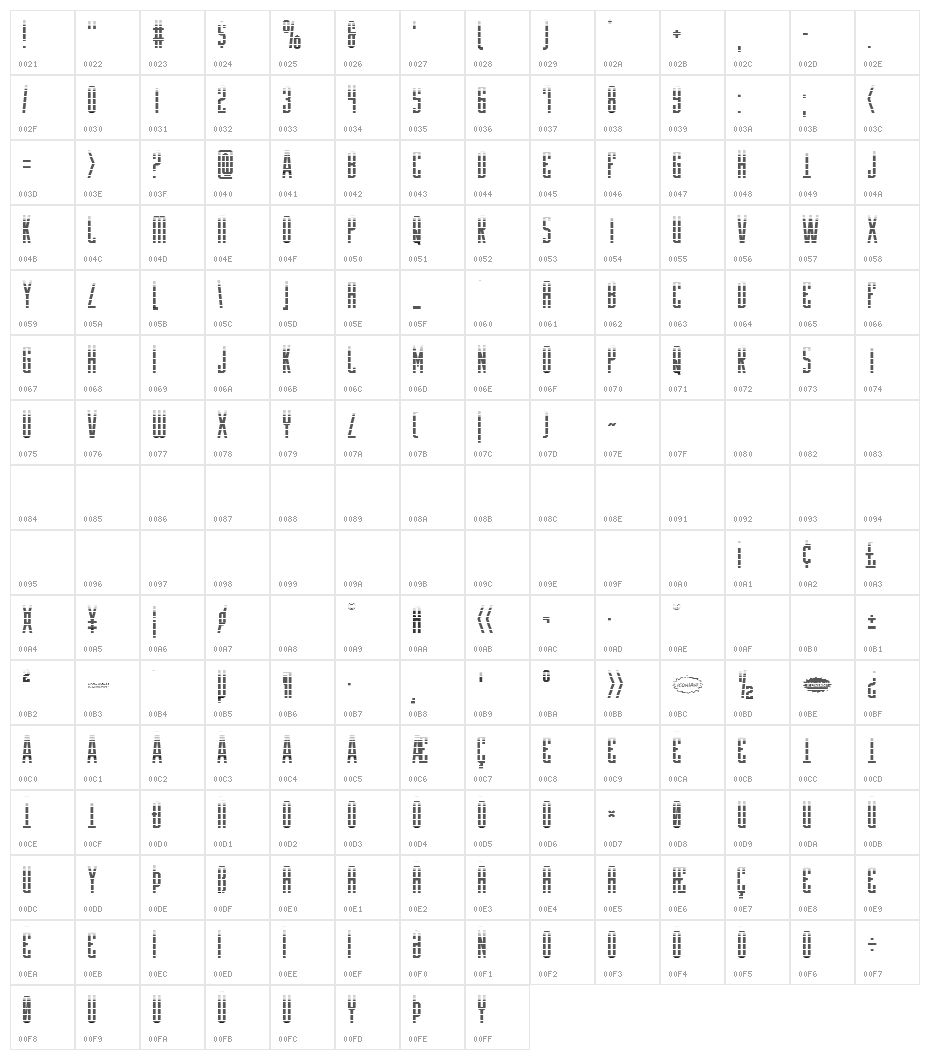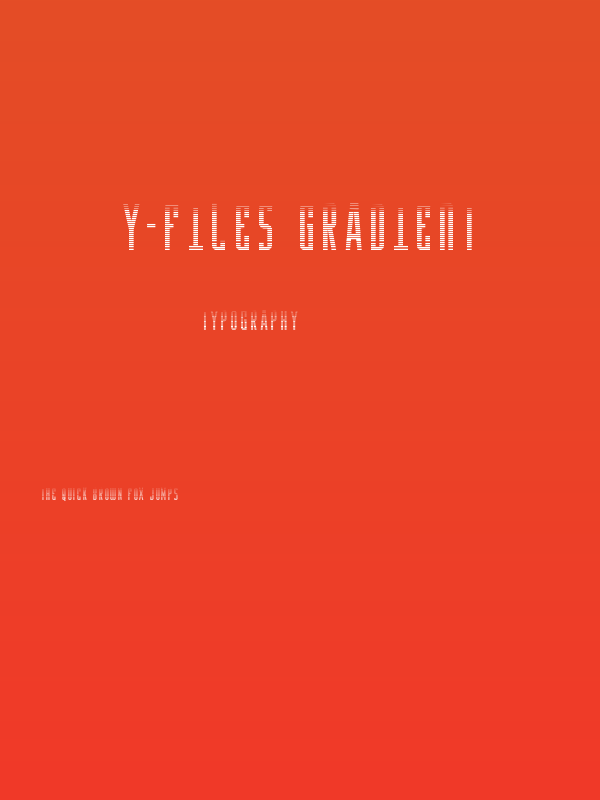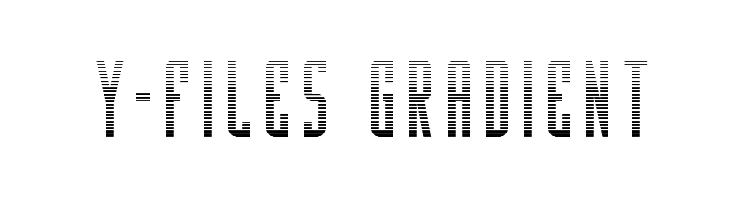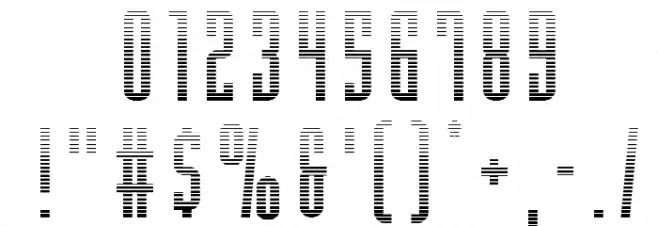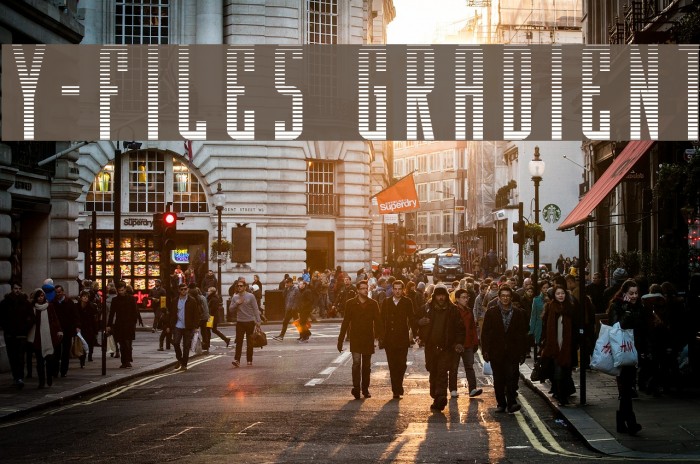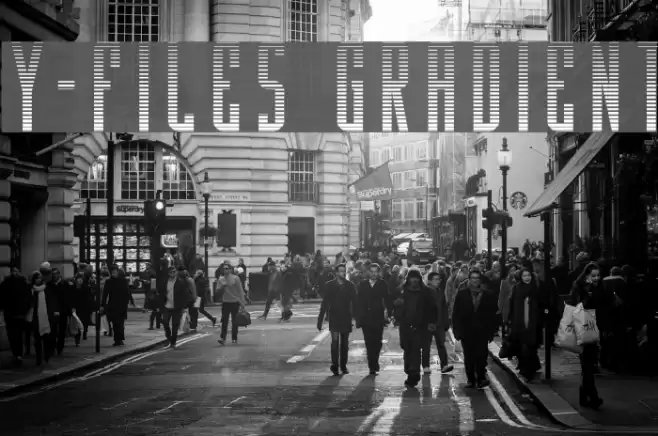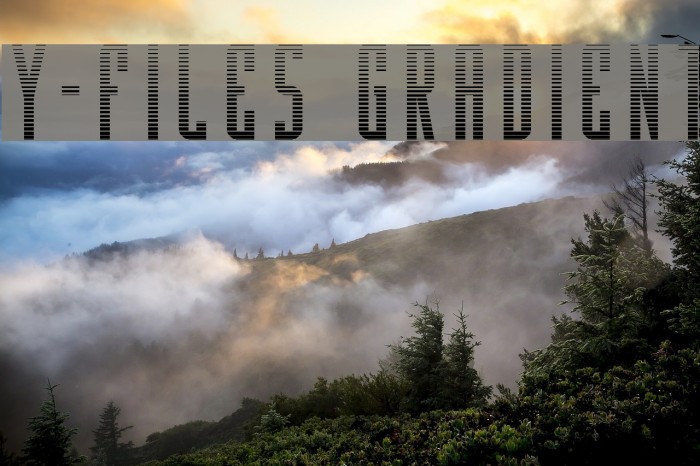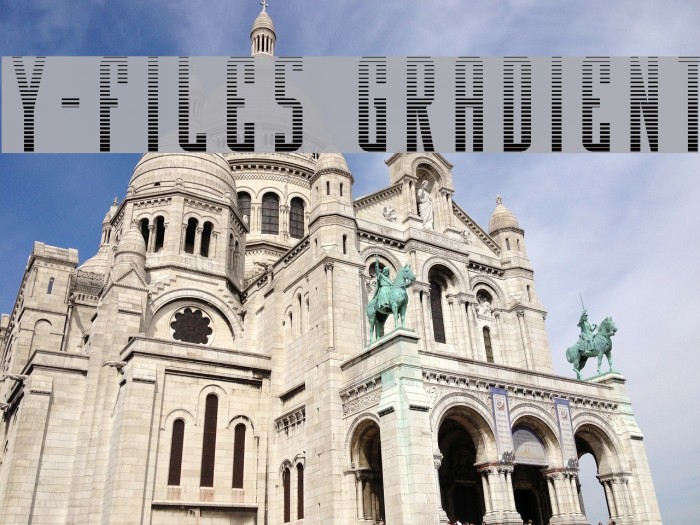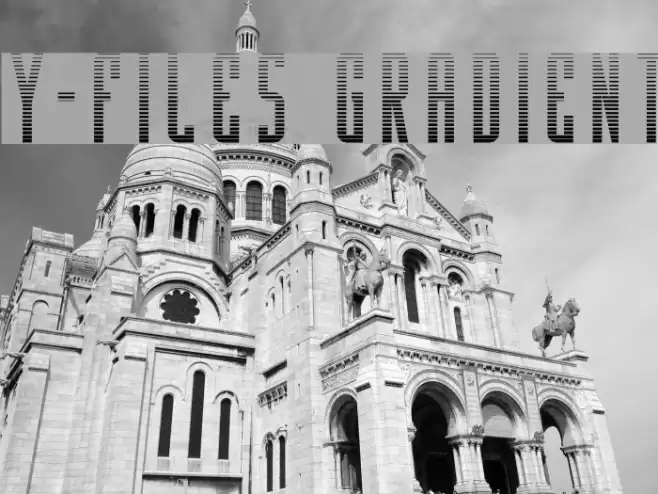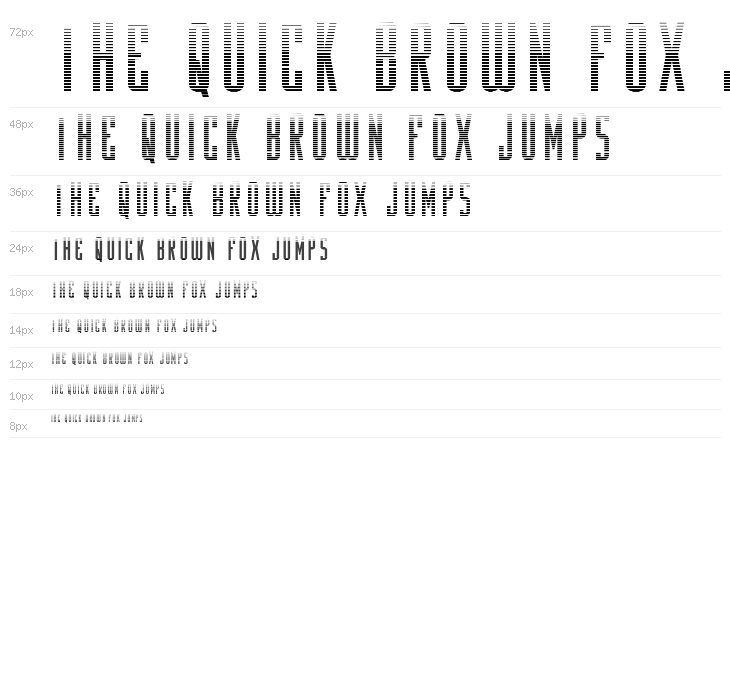
Y-Files Gradient Font
| Vorgeschlagene Projekte | Ideal for futuristic designs, tech branding, posters, and digital media where a bold, modern look is desired. |